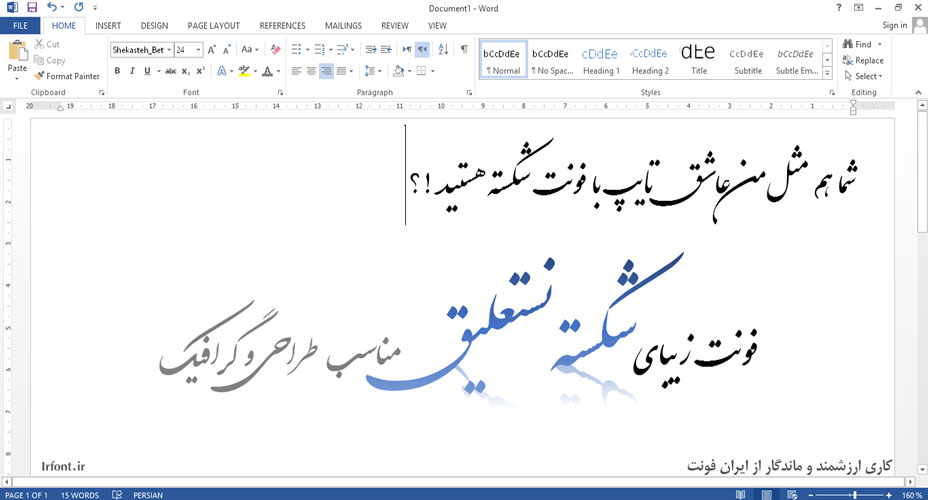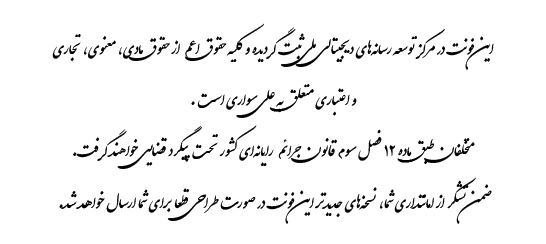
یک فونت شکسته نستعلیق واقعی
shekaste
این فونت شکسته نستعلیق در سال 1391 توسط علی سواری ساخته شد. این فونت پنج زبان مهم (اردو، عربی، فارسی و پشتو) را ساپورت می کند و در برنامه هایی که open type ساپورت هستند عمل می کند. این فونت برای نخستین بار در وب سایت ایران فونت برای فروش عرضه شده است.